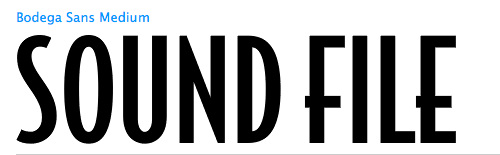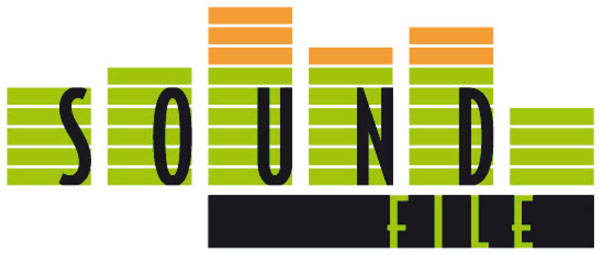
Schrift ähnlich Gill Sans Condensed
Ich muss demnächst eine Homepage erstellen und habe vom Auftraggeber nur ein Logo, dass in einem Word-Dokument natürlich mittelmäßig aufgelöst eingebettet war. Ich möchte diese relativ einfache Logo nachbauen und es hakelt nur an der richtigen Schrift.
Whatthefont kann damit nichts anfangen. Ich habe selber schon die Richtung ITC Anna oder Gill Sans Condensed vermutet. Letztere würde es gut treffen, aber die Abstriche am großen S passen nicht so ganz (Gill ist gerade, hier aber schräg). Die Querstriche an F und E sind wohl eher hinzukonstruiert.
Hat noch jemand eine andere Vermutung, welcher Font passen könnte?